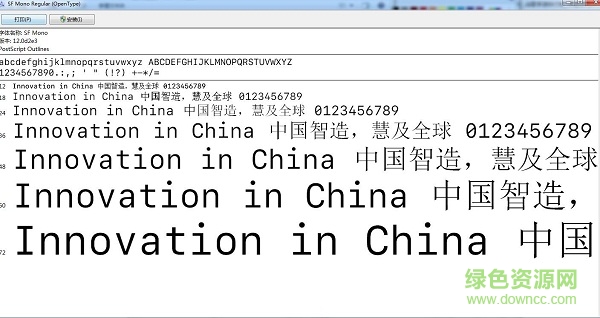
sf mono regular字體
sf mono regular字體是一款非常實用的英文等寬字體,每一個單詞的線條筆畫都很清晰,可讀性強(qiáng),多用于編程或是網(wǎng)頁設(shè)計,歡迎大家免費(fèi)下載!
等寬字體特點(diǎn)
因早期的電腦顯示器、打字機(jī),由于技術(shù)的局限,無法進(jìn)行字母寬度的比例調(diào)整,因此將每個字元都制作成一樣的寬度,從而形成了等寬字體,在等寬字體中,字母i,j顯得兩側(cè)馀白較多,而字母w,m等的筆畫顯得相當(dāng)擁擠。